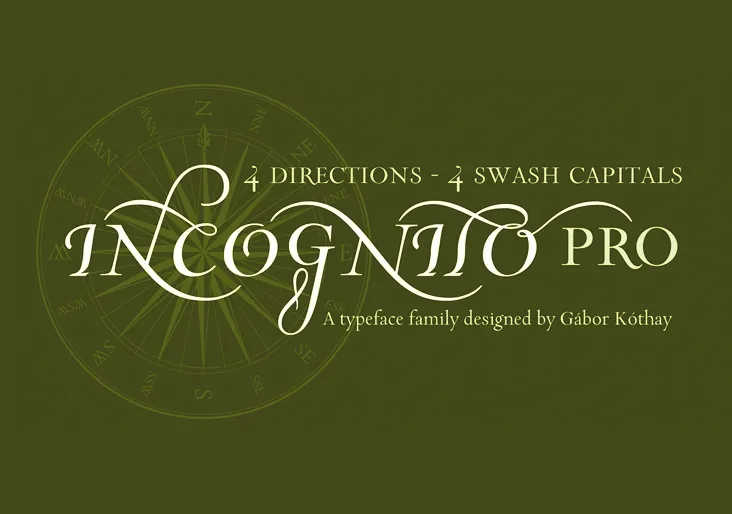
Descubra uma nova aventura no mundo das fuentes digitais com Incognito Pro Font Family. Esta família de serif foi criada para aqueles que buscam algo mais significativo, algo que ressoa com as histórias e tradições passadas. O designer 178-MC mergulhou em seu passado húngaro e na rica cultura do folclore dos tempos antigos para inspirar o design deste conjunto de letras. Incognito Pro inclui uma variedade impressionante de fontes que vão desde tipos leves até formas mais robustas. O nome da família foi inspirado nas denominações geográficas presentes nos mapas, enquanto as variações com swash foram nomeadas em homenagem aos termos latinos para os pontos do compasso. Este é um projeto fascinante que oferece uma paleta de opções ideais para a criação de designs profissionais e criativos, tornando Incognito Pro Font Family uma escolha inteligente para quem busca qualidade e história em cada página impressa ou digital.